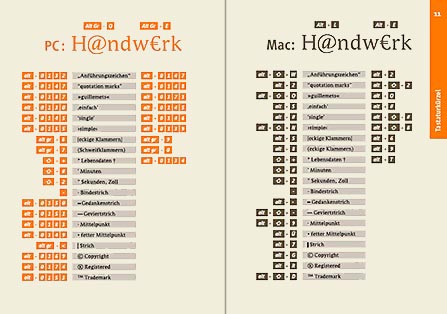
deutsche „Anführungszeichen“ am Mac: vorne alt-shift W, hinten alt 2 am PC: vorne alt-0132, hinten alt-0147 englische “quotation marks” am Mac: vorne alt 2, hinten alt-shift 2 am PC: vorne alt-0147, hinten alt-0148 französische »guillemets« am Mac: vorne alt-shift Q, hinten alt Q am PC: vorne alt-0187, hinten alt-0171 ![]() Dank der kostenlosen Designer-Formelsammlung »Apfel i« finden FontShop-Kunden an Macs und PCs immer die richtigen Häkchen und Öschen Herausgegeben: Do - Juni 16, 2005 at 01:37 nachm. | |